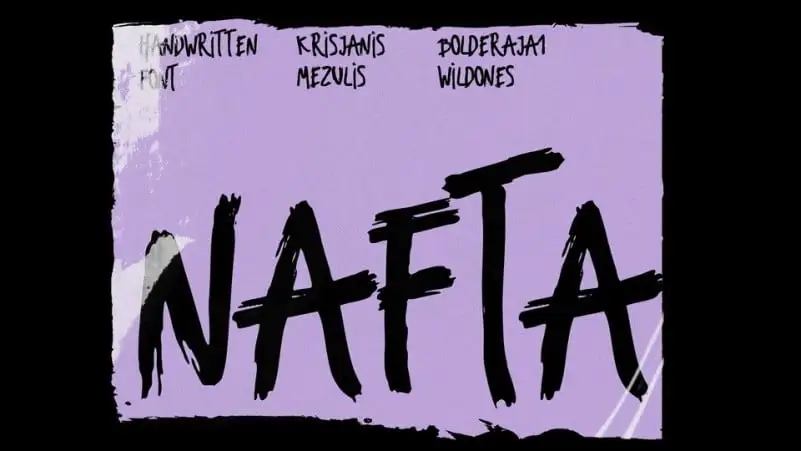
Nafta Brush Font – Download Grátis
A Nafta Brush Font é uma elegante tipografia script, perfeita para qualquer projeto profissional que exige design sofisticado. Combine-a com textos escritos a mão e você criará um design poderoso e atraente. Criada por Krisjanis Mezulis, esta fonte de tipobrush está disponível gratuitamente. Ela representa formas desenhadas livremente misturadas com o posicionamento ondulante entre cada letra. A Nafta Brush Font é uma opção perfeita para designers que buscam um look moderno e moderno, que combina elementos modernos e antiquados em uma única fonte. Sua qualidade limpa e sua aparência deslumbrante garantirão que seu projeto seja destacado, tornando-a a escolha certa para qualquer projeto profissional.